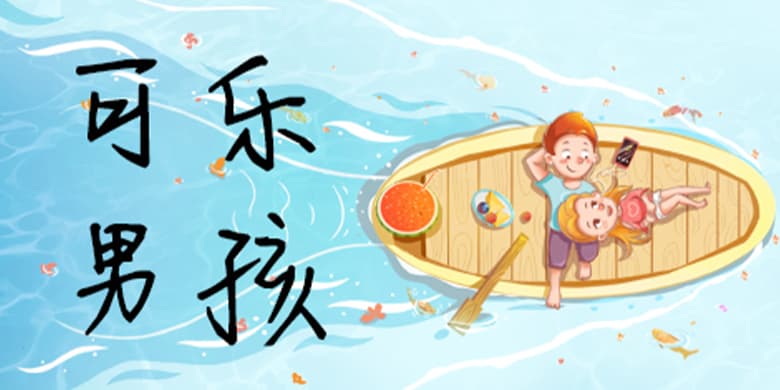
方正手迹-可乐男孩
品牌:方正手迹设计师:张妮发行时间:2020字库编码:大陆简体(GB2312-80)分类:常规书写·硬笔字体属性:精品字
方正手迹-可乐男孩
这款字结构灵活,起笔收笔都有讲究,笔意连贯,气韵悠长,英气与洒脱兼备,让人百看不厌。适用于文艺类的书刊、品牌广告和产品包装设计,以及社交网络的个性化用字。